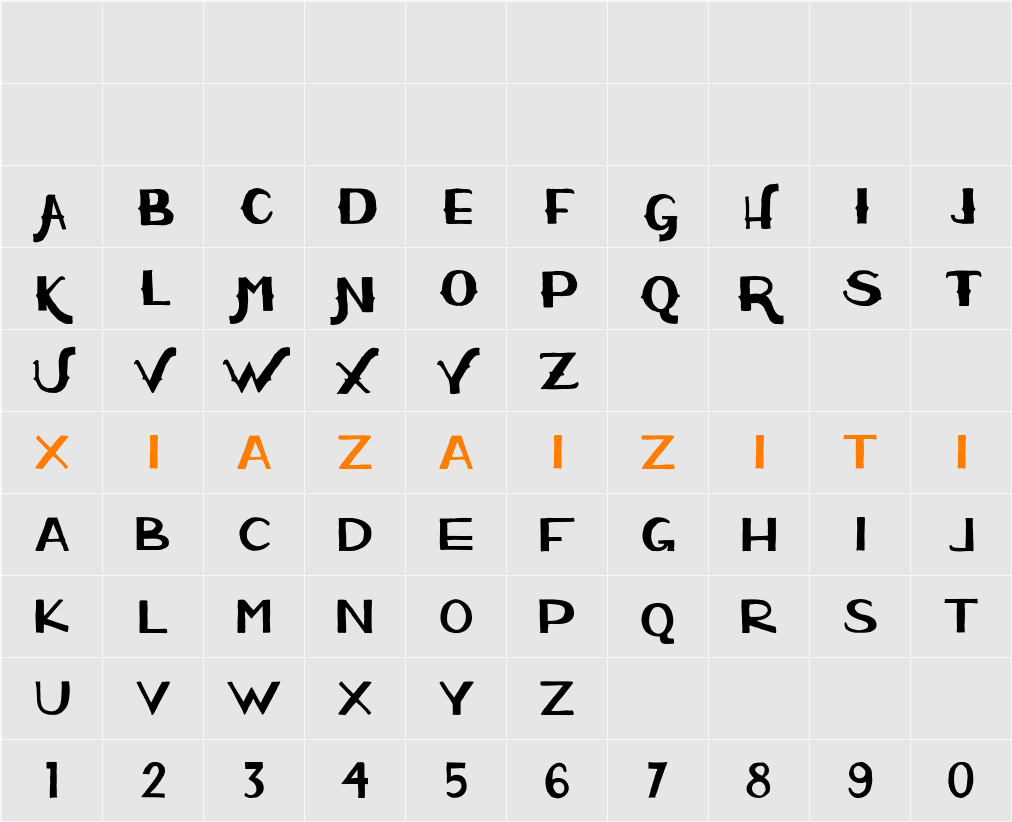
Wolder
Wolder,这款字体结构工整、笔画清晰,兼顾美观与易读性,适用于标题、正文、海报、包装、LOGO 等多种场景。字形优雅稳定,风格百搭耐看,适配日常排版与创意设计,让文字呈现更舒适、更具质感。Wolder一笔一画,皆是细节,以均衡的比例、流畅的线条打造舒适视觉体验,字形端正大气,风格简约现代。无论是商业设计、品牌宣传还是日常排版,都能轻松驾驭,让文字更有格调与力量。Wolder字体下载。
• 字体名称: Wolder